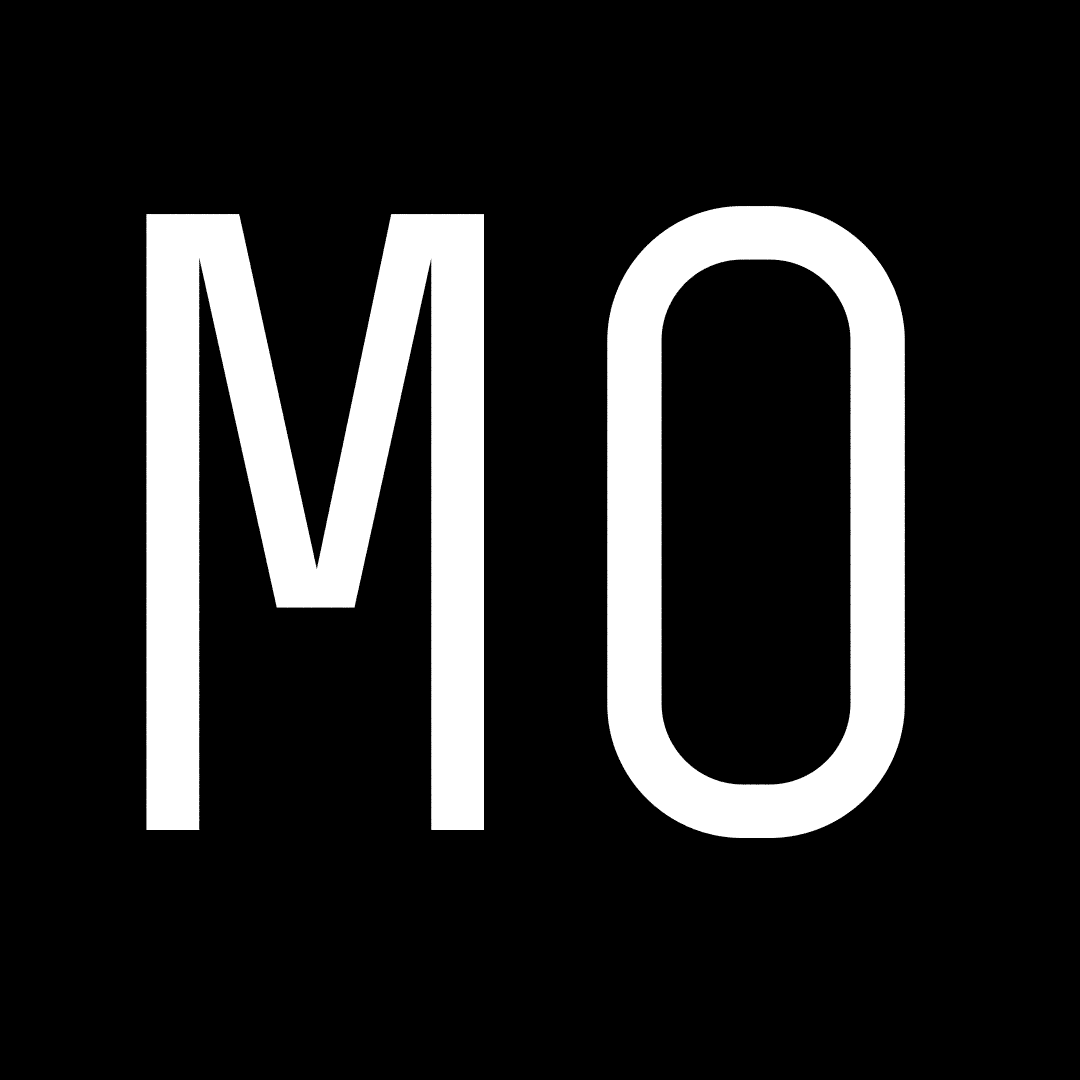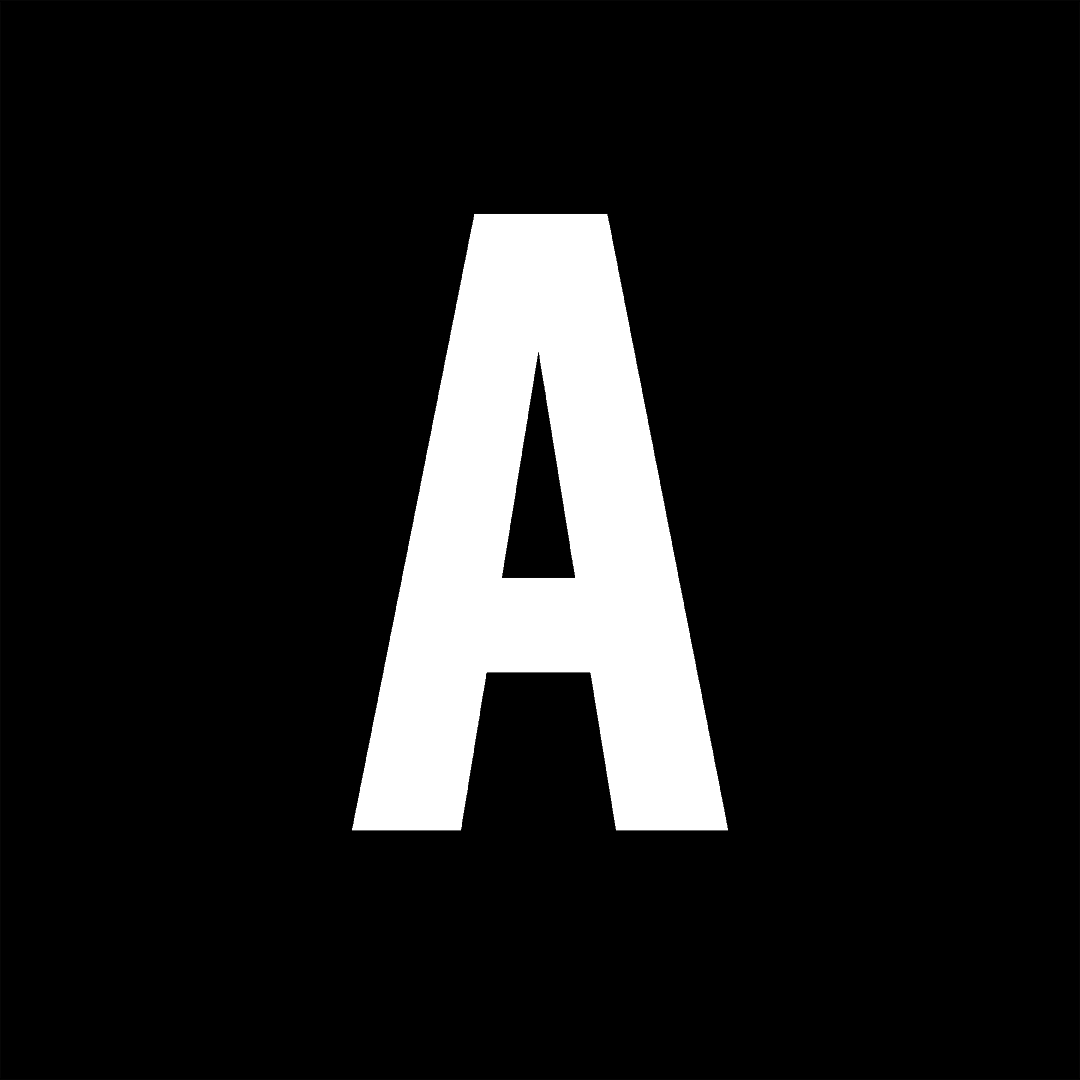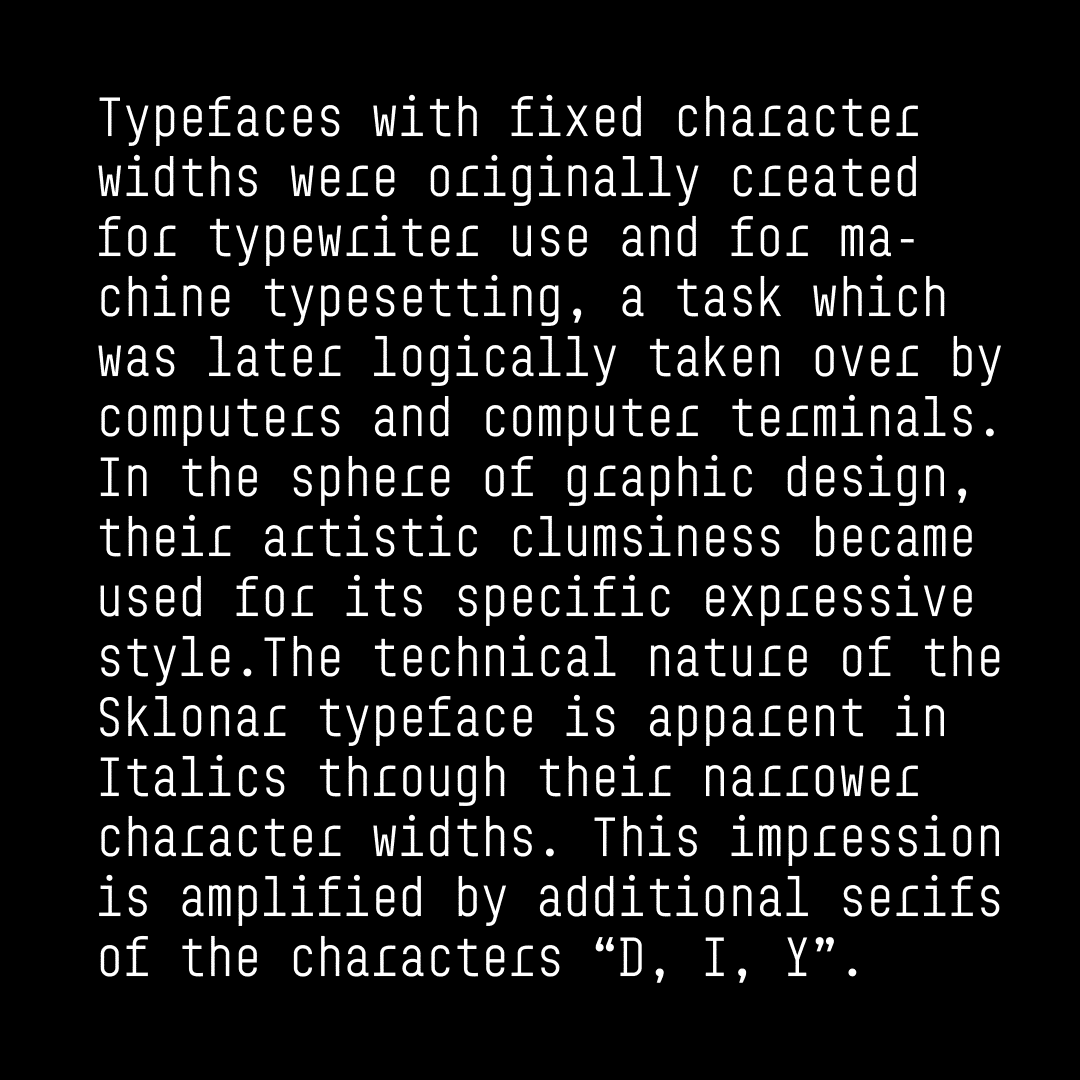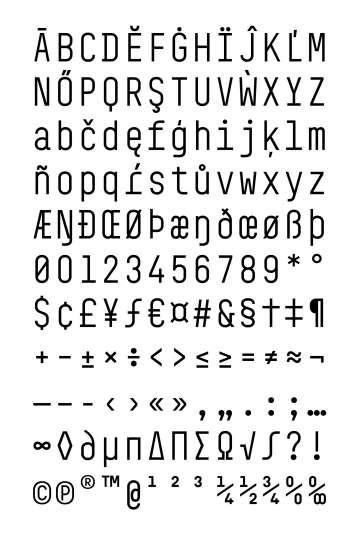
Sklonar
Galerista Zdeněk Sklenář otevřel v roce 2011 na pražském Smetanově nábřeží bílou krychli jednoduše nazvanou S. Prostota prostoru architekta Josefa Pleskota se odrážela i v drobných kartičkách pozvánek, které uváděly vždy různou číselnou hodnotu odvozenou z vystavených děl (například barevnou RGB hodnotu malby). Galerii po dvou letech rozmetal výbuch plynu v sousední budově, ale technicistní písmo studio používá pro další a další projekty – asi nejčastěji z víc než dvacítky písem, které tu vznikly. Charakteristickými znaky Sklonaru jsou znaky „D, I, Y“ s delšími patkami. Svislé, otevřené zakončení tahů malých písmen „f, g, j, r, t“ a „y“ vnáší do jinak geometrické kresby lehkou dynamiku. Pravidelné „s“ je v příjemném kontrastu k výraznému „a“. Hravost abecedy podtrhují výrazné tvary interpunkce a diakritiky. Sklonar je rafinované písmo, které se na první pohled zdá přísně geometrické, bližší pohled ale odhalí překvapivé živé detaily. Může být nasazen nenápadně, nebo tak, aby poutal okamžitou pozornost. Naposledy jsme ho použili na koloběžky.
Designer: Marek Pistora, Martin Vácha